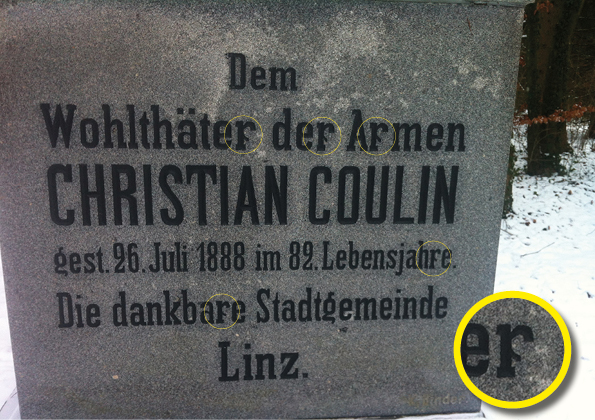
Eigenartige Serife Coulindenkmal Stadtfriedhof Linz
Beim Weihnachtsspaziergang am Stadtfriedhof Linz in St. Martin ist mir beim Coulindenkmal eine Besonderheit im kleinen r der Beschriftung aufgefallen. Es hat eine zusätzliche Serife (?) rechts beim Aufstrich etwa in der Mitte der x-Höhe. So etwas ist mir noch in keiner Schrift aufgefallen. Ist das eine alte (heute nicht mehr gebräuchliche?) Weise das r zu meißeln? Oder ist das eine spezielle Exaltiertheit des Steinmetzes gewesen?
Oder ist das eine spezielle Exaltiertheit des Steinmetzes gewesen?
Sicher etwas in der Art. Ein Dorn, wie man ihn sonst eher von Western-Schriften kennt. Aber warum nun ausgerechnet nur am r? Nicht daß der Gute beim ersten r mit dem Werkzeug ausgerutscht ist, und das dann durchziehen mußte, um erklären zu können, daß das kein Bug, sondern ein hochmodisches Feature ist?
Danke, Jan-Albert für die schönen Flickr-Beispiele. Ergibt grundsätzlich Sinn, dass es aus dem Schwung des rechten Teils des r heraus entstanden ist. Als ein Überbleibsel aus der Kurrentschrift kann ich es so direkt nicht erkennen, vielleicht aber deswegen, weil ich diese Schrift nur marginal verstehe.
Ich habe derartige r auch schon öfter bei Schildermaler-Schriften gesehen, und glaube auch nicht, das dies aus einem Misgeschick heraus geschah, sondern eher, um den doch recht groß werdendenb Weißraum unter dem r ein wenig zu füllen.
Viel gebracht hätte es dann ja nicht.
Hätte der Steinmetz dann nicht einfach den Schweif des r kürzer machen können, wenn es ihm darum gegangen wäre?
Sicher hätte er das, aber die Schrift hat ja außer dem r noch so ein paar Spezialitäten, wie diese 92-Ligatur als 2, oder dieses "Kriechkeller-g"
Irgendwie haben wir hier grad die Linzer Typo am Wickel?
Interessant ... Fiel mir irgendwie noch nie auf ...
Apropos ...
"Kriechkeller-g"
Auf der flickr-r-Seite ist auch ein nettes g dabei, falls es mal unten eng wird ...